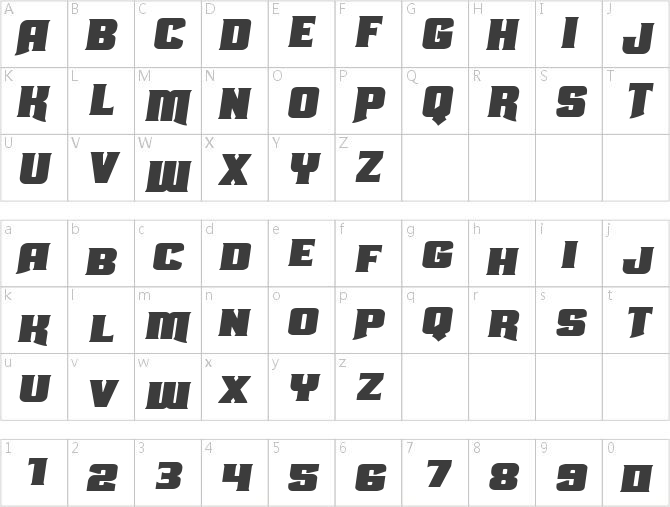
uniongrayexpandsemital
uniongrayexpandsemital介绍
uniongrayexpandsemital字体字库是一款让人赏心悦目、百看不厌的英文字体,适合各类广告和产品包装设计应用,字体大小0.04MB,格式为ttf字体,上传用户是众联齐成,作者/版权方为未知